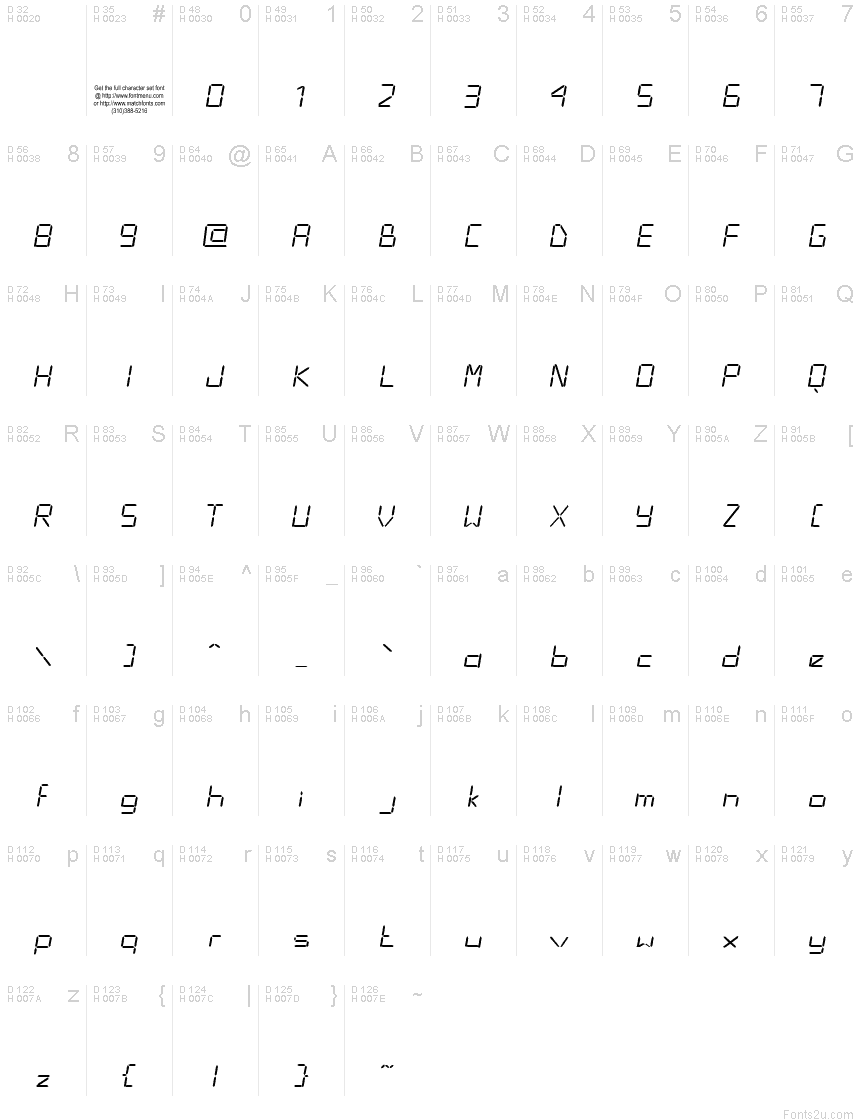
CristoLikid od M.Bujardeta z Match Software to darmowy cyfrowy krój typu display, który zamienia segmentowane litery w coś zaskakująco płynnego. Każdy znak zbudowany jest z krótkich, prostych kresek przypominających wyświetlacze kalkulatorów i zegarów LED, jednak delikatne nachylenie i zaokrąglone łączenia sprawiają, że całość wygląda, jakby była w ruchu. Efektem jest wyrazisty, techniczny wygląd z nutą eksperymentalnej zabawy – niczym sprzęt retro w nowym wydaniu dla interfejsu science-fiction.
CristoLikid to futurystyczny styl, który świetnie sprawdza się w tytułach gier, nakładkach interfejsów, grafikach muzycznych, plakatach technologicznych, okładkach książek sci-fi oraz w odważnym brandingu. Ten darmowy font najlepiej prezentuje się w dużych rozmiarach, gdzie jego segmentowa struktura jest czytelna i sprawia wrażenie celowo mechanicznej. Połącz go z czystym bezszeryfowym krojem geometrycznym w tekście głównym i pozwól, by CristoLikid przejął główną rolę w logotypach, nagłówkach i elementach nawigacyjnych.